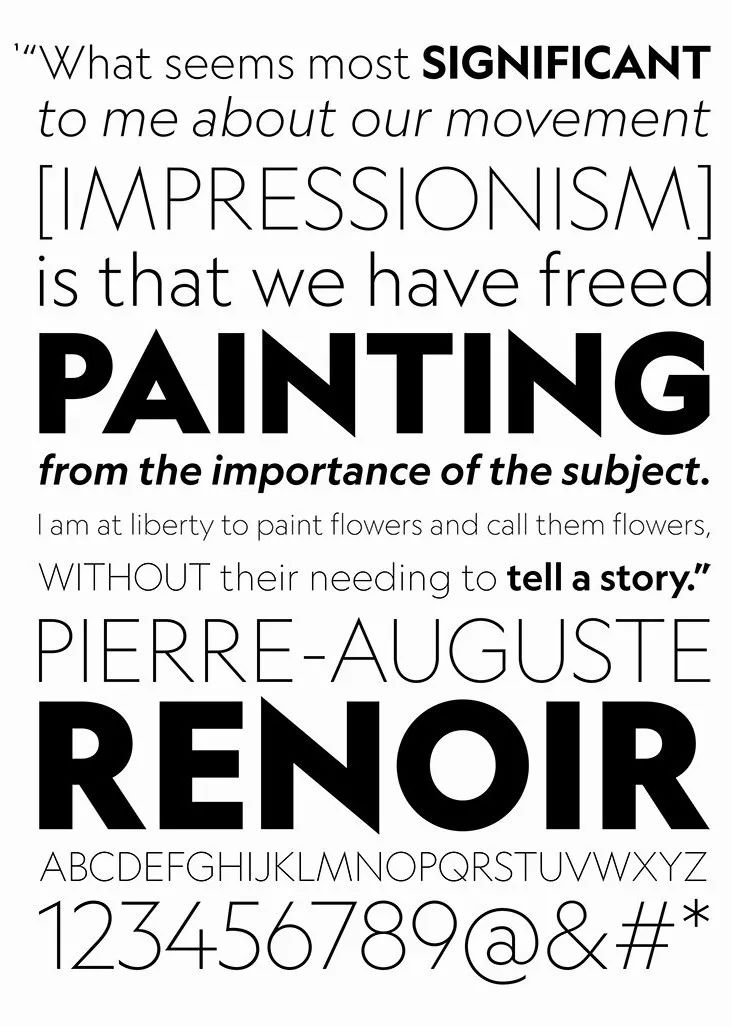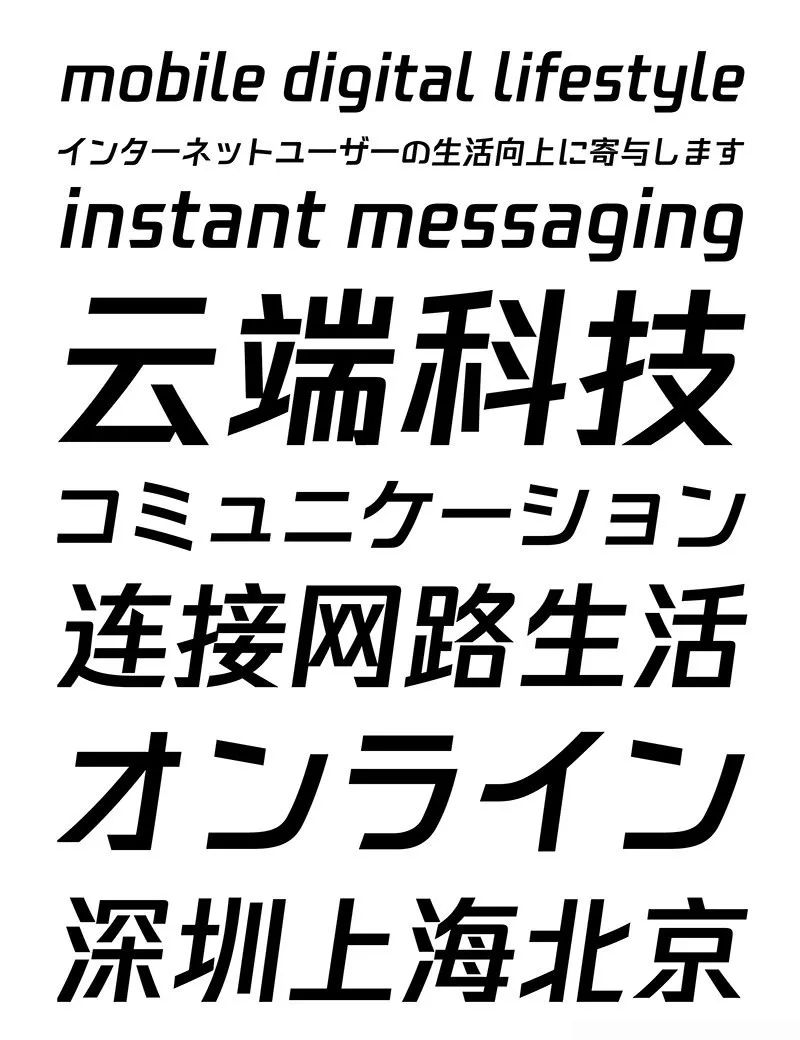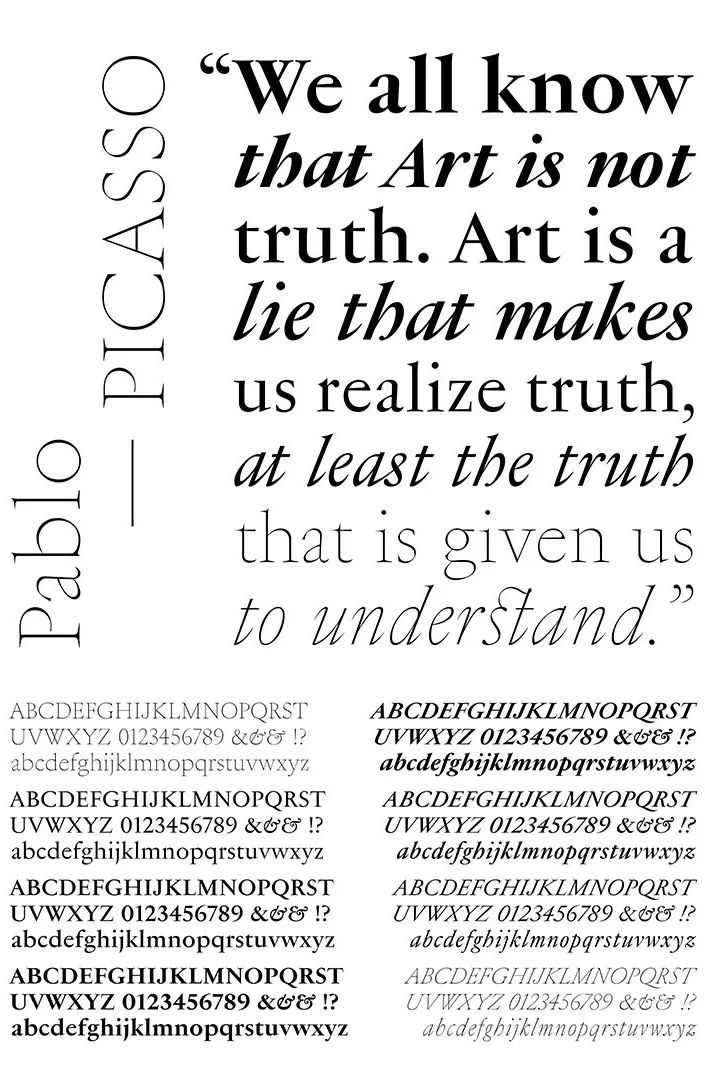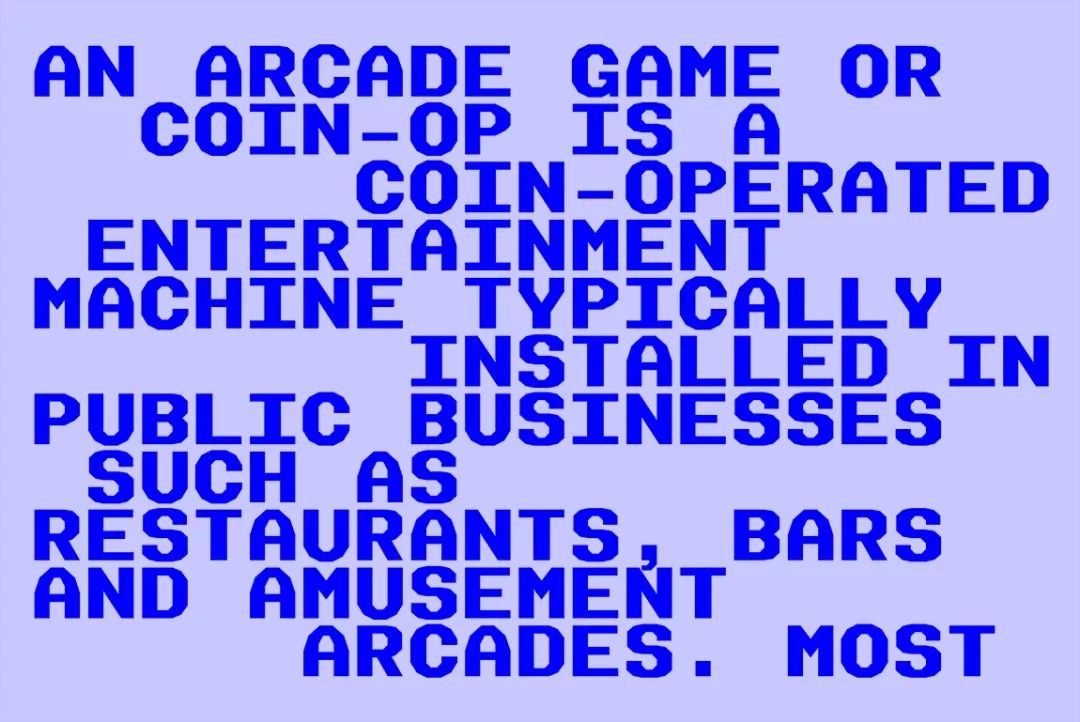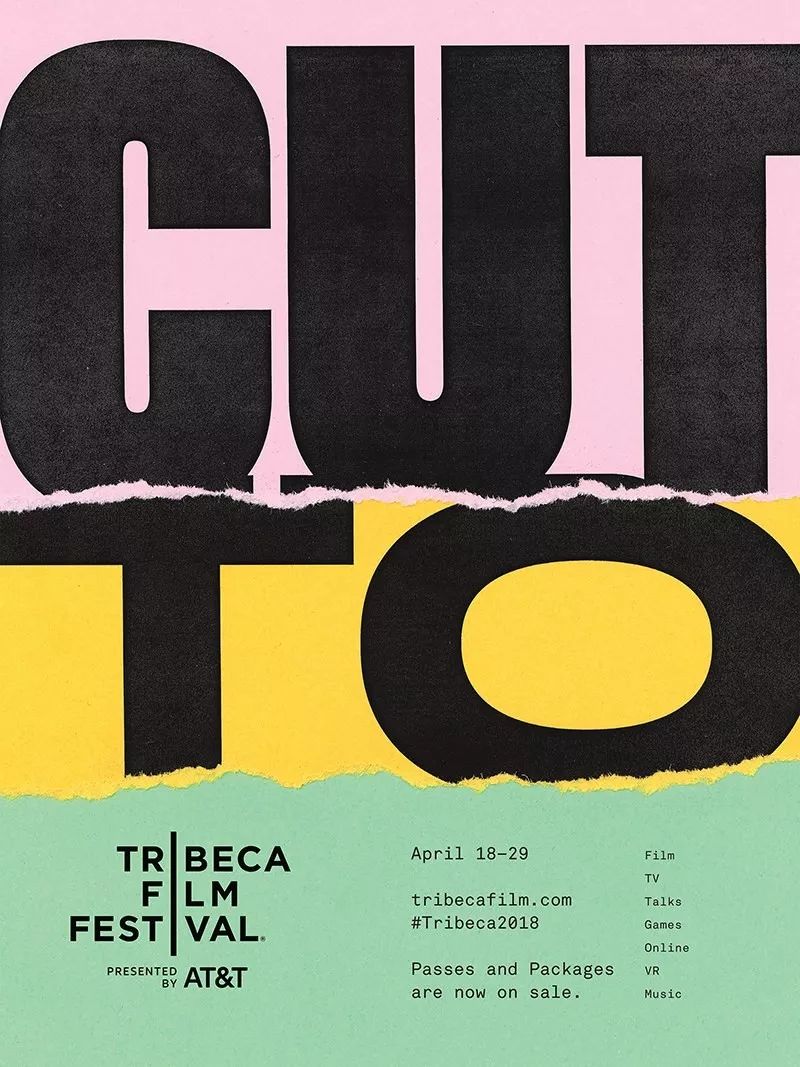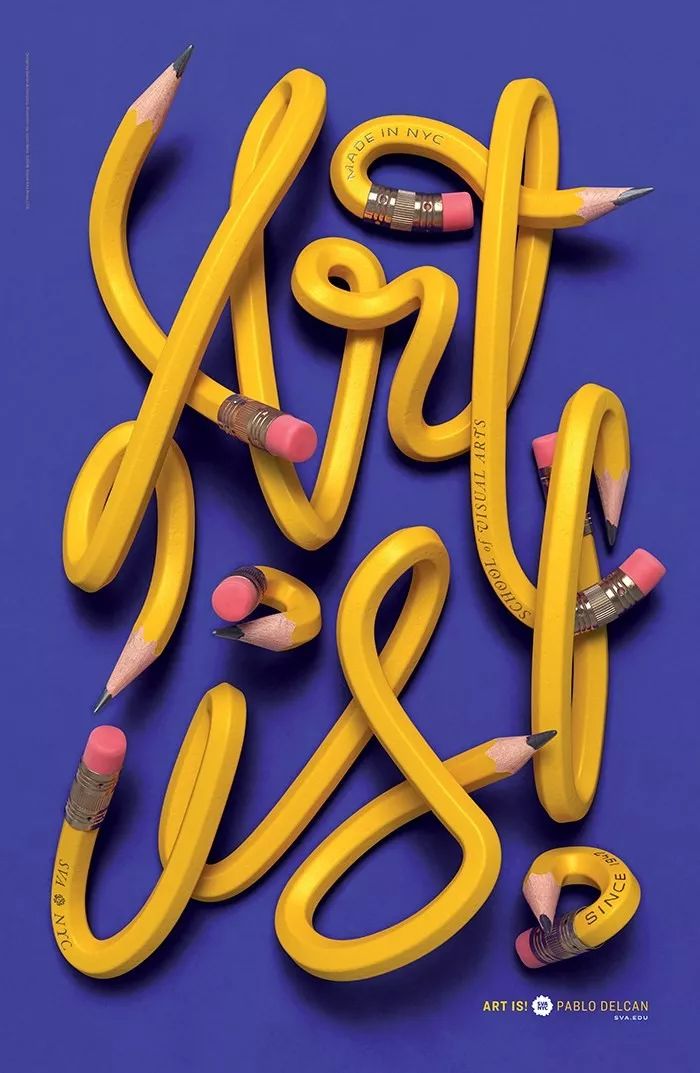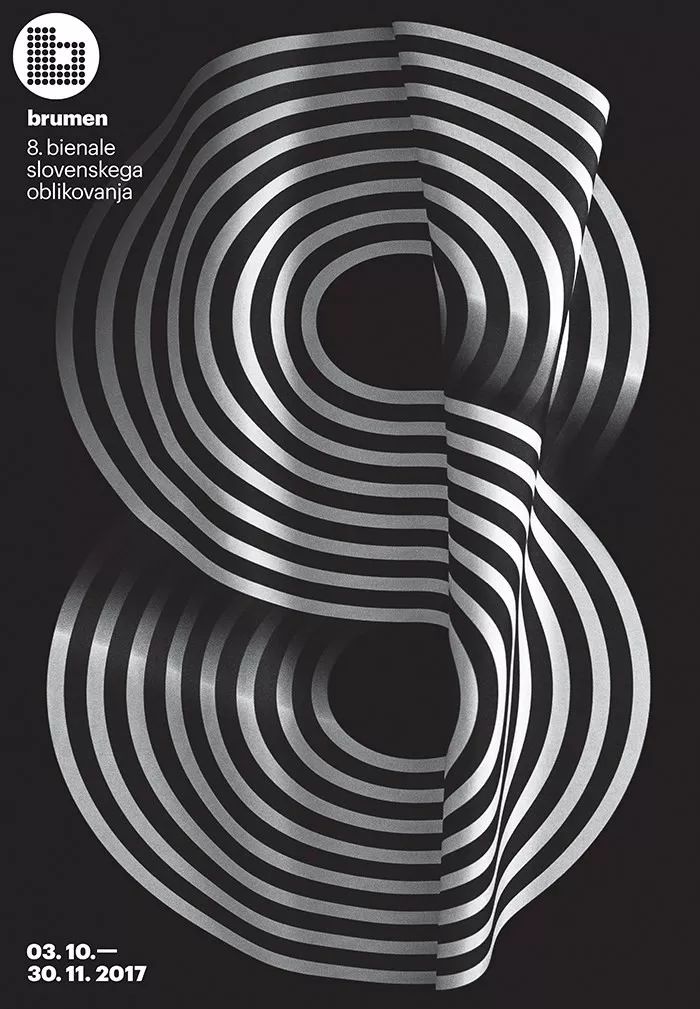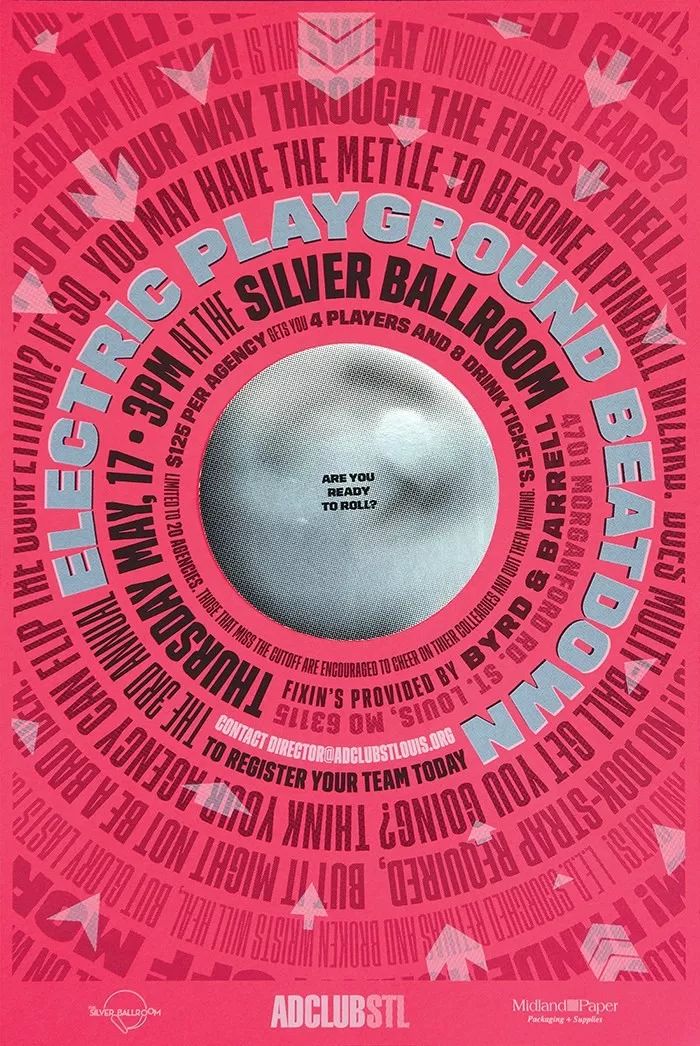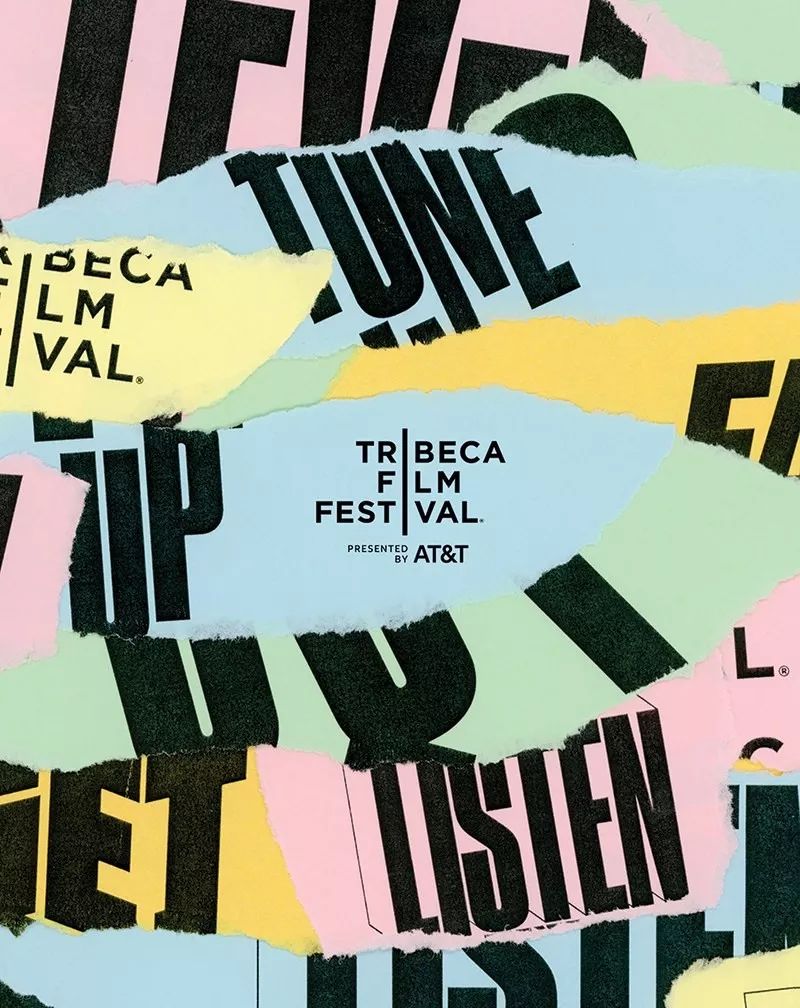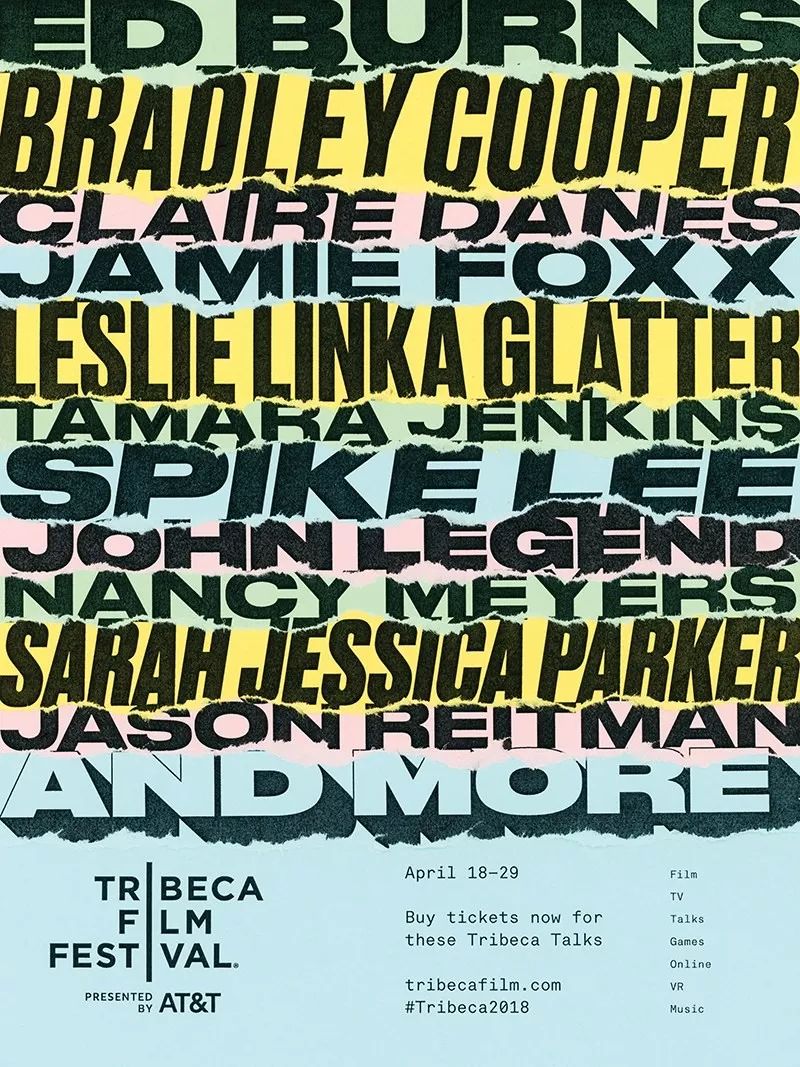
Communication Arts公布年度最佳字体设计
自1959年以来,Communication Arts一直致力于出版全球最佳视觉传播,现在线上展示画廊已经开启,作为全球创意人交流和展示的平台。CA的社论、专题文章和各类别年度竞赛不断产出新的创意,为创意领域从业者提供更多的机会,同时也提升了该领域的最高专业标准。
关于Communication Arts赛事
Competitions
Communication Arts官方赛事涵盖整个视觉传播领域,面向全球的设计师、插画师和创意人,包括学生群体。
分为六大赛事类别:字体(Typography)、交互(Interactive)、广告(Advertising)、设计(Design)、摄影(Photography)、插画(Illustration)。
2019 Typography Competition
2019年度字体设计评选出的作品非常精彩,从企业字体定制到海报版式再到各式出版物,行业类别跨度很大;再者是位于全球前列的大型企业推出了几款精彩的定制字体,也在赛事中脱颖而出得到出版及展示的机会。并且,这是一场面向全球的赛事,今年在得到展示的学生作品中,也有中国高校学生的精彩作品。
2019年度字体选登
字体设计
Typeface Design
腾讯定制字体
Tencent Sans
字体设计师:Ryota Doi / Sammy Fung / Julius Hui / Robin Hui / Juan Villanueva
《国家地理》定制字体
Geograph
字体设计师:Kris Sowersby,Klim Type Foundry
路易·威登集团定制字体
LVMH
字体设计师:Hugues Gentile / Jean-BaptisteLevée / Quentin Schmerber
Kill Screen
一款概念性的显示字体,是为Radix的视觉系统创作的,Radix是一个禁止药物滥用的协会。使用吃豆人游戏中的角色作为药物滥用的隐喻,因为它不停地吞噬,玩得开心但最终变成鬼魂。字体旨在以现代方式体现街机游戏的精神,充满乐趣但表达严肃的主题。
设计师:Alfio Mazzei;Alfio Mazzei / Pete Rossi,创意总监
广告印刷
Print Advertising
像Ozzie一样翻转
Flip Like Ozzie
为了纪念菲利普斯在圣路易红雀队主场布希体育场举行的66天比赛,我们与Ozzie Smith合作,Ozzie Smith是以著名后卫翻身而闻名的球手。凭借绿屏和计算机技术,我们创造了一个游戏体验,帮助每个人#FlipLikeOzzie。
设计师:Andrew Wetzel;设计总监:Milton Un
Tribeca电影节海报
Tribeca Forward
将电影剧本的语言表达形式与水墨印刷、撕裂纸张的质感结合。
艺术总监:Avni Jain / Juan Miguel Marin / Eduardo Palma / Luke Williams
231 S LaSalle
一场为媒体营销活动创作的版式,利用报纸媒体重写被认为具有新闻价值的内容。
设计师:Jimmy Hansen;艺术总监:Brock Haldeman
Posters
SVA地铁海报
Pablo Delcan SVA Subway Poster
设计师:Pablo Delcan,Delcan&Company
年度弹球锦标赛
Annual Pinball Tournament
设计师:Ashford Stamper
第8届布鲁门双年展
8th Brumen Biennial
古典音乐会系列海报
Les Concerts du Mercredi 2017-2018
现场音乐会与音乐录音不同,空间和时间使每一场演奏都独一无二,这也是海报设计的理念。我们开发出一种生成设计,可以制作750张独特的海报。
字体设计师:Cédric Rossel;艺术总监:Cédric Rossel/Sophie Rubin
夏季设计研讨会
Summer Design Seminar
设计师:David Jones
乒乓王竞赛
King Pong VII
设计师/艺术总监:Alex Bakker / Pamela Rounis
北美音乐节海报
Ravinia Festival 2018
设计师/艺术总监:Michael Braley
学生作品
Student Work
Verso Books
Verso Books是一个独立出版社,1970年创立。今天,Verso每年发行100多刊出版物,重点关注政治、哲学和文化。
设计师:Jack Burnside
爱因斯坦的梦想
Einstein's Dreams
这本实验书籍重新构想了艾伦·莱特曼(Alan Lightman)的小说《爱因斯坦的梦想》中的一章,通过立体结构、网格材料和重新排版进行实验设计。
印刷师/设计师:Meagan L. Vanderhill
制造些噪音
Make Some Noise 2018
设计师:Hsin-Ho Hsieh/Chang-Wei Huang/Sung-Che Huang/Yu-Chen Huang/Ju-Fang Liu/Li-Fang Tseng/Yuan-Ting Tung/Yu-Quan Zhang
22条军规
Catch-22
Catch-22是一本关于战争悖论的讽刺书。为了表达这一点,创作一个具有不同含义的封面,具体取决于书的转动方式。当这本书正面朝上时,它描绘了一架被轰炸的飞机的图像; 但当这本书倒置时,飞机正在投下炸弹。
设计师:Cooper H. Weinstein